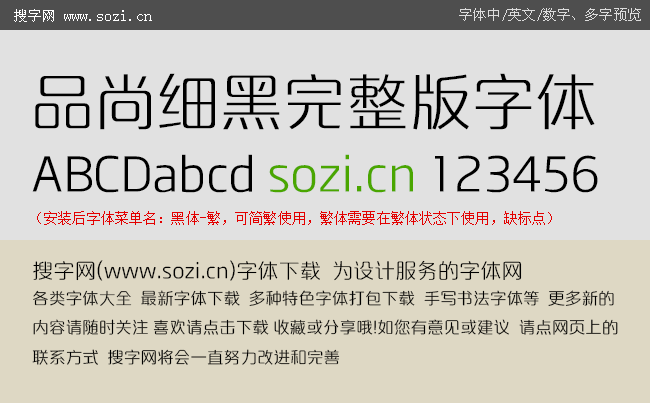
品尚細黑完整版字體
搜字網(wǎng)給大家提供一款品尚細黑完整版字體手機中文字體下載。方正"品尚黑"系列字體繼承了黑體粗黑均勻、字體端莊、莊重醒目的優(yōu)點,同時橫豎略作粗細變化、橫略細于豎的手法,撇捺挺拔銳利,與轉(zhuǎn)折處優(yōu)美圓潤的弧度形成反差,并去掉了傳統(tǒng)黑體的喇叭口,也增強了時尚感。適合喜歡簡潔的朋友在手機上安裝使用。